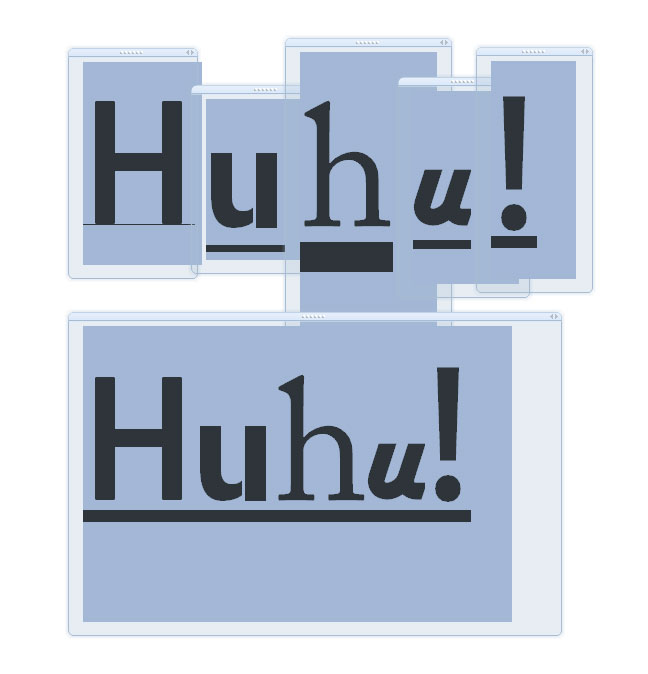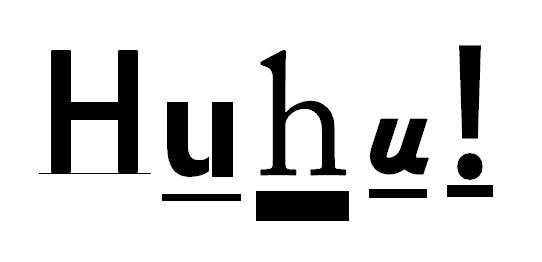
Unterstreichung im Font festlegen?
Gerade habe ich mal eine Grundsatzfrage - kann sein, dass das eine "Anfängerfrage" ist, ich bin bloß grad relativ verwirrt ...
In Office-Programmen oder auch hier im Editor hat man ja die altbekannten Knöpfchen "B", "I" und "U". Während nun bei "I" ja meistens noch vom Betriebssystem ein entsprechender Italic-Font aus der Familie geladen wird, rätsle ich nun gerade, woher dann diese Unterstreichung kommt, da es offensichtlich ja keinen "Underscore-Font" gibt.
Hier muss also scheinbar irgendetwas "klammheimlich automatisch" gemacht werden.
Oder aber: legt man irgendwo im Font fest, wie bei einer Unterstreichung verfahren werden soll?
Es scheint ja nicht irgendwie das Betriebssystem nach Belieben zu machen, sondern die automatische Unterstreichung ist schon durchaus Font-abhängig; hier ein typografisch unglaublich wertvolles Beispiel zu Veranschaulichung:
Könnt ihr mir sagen, wo dazu die "Stellschraube" ist? Bzw. wie das mit dem Unterstreichen eigentlich funktioniert? Wie läuft das ab? Wie kann man da etwas beeinflussen (Lage, Dicke, ...) beim Erstellen eines Fonts?
Im Font kann das global definiert werden – wo ist die Linieund wie dick ist sie.
Dass das alle Hersteller auf sinnvolle Werte einstellen, kann man vermutlich anzweifeln.
Was die Anwendungsprogramme daraus machen, ist unterschiedlich.
Ich hab das jetzt nicht erforscht, aber ich würde annehmen dass in einem Programm das "auf Knopfdruck" unterstreicht das Auslesen dieser Werte sinnvoller ist und deinem Beispiel nach auch funktioniert, während in einem Grafikprogramm, in dem ich als Setzer vermutlich selbst definieren will, wo, wie dick und in welcher Farbe die Schrift unterstrichen wird, diese Sache eher kontraproduktiv wäre. Indesign interpretiert die Vorgaben jedenfalls nicht ...
Komisch, ich habe festgestellt, dass InDesign die Unterstreichungswerte aus die Schriftdatei einlesen und diese richtig umsetzen. Habe es gerade für die TheSerif, FF DIN, Rotis (AT), ITC Garamond (URW) und Minion getestet. Das Zeichen Underscore und der Stil »Unterstreichen« ergeben bei gleicher Schrift die gleiche Striche an gleiche Positionen. Ist aber anscheinend (leider) kein Standard. Bei Arial, Arno und FF Celeste sitzt die Unterstreichung höher als das Underscore …
In QuarkXPress war es in Versionen wie 2, 3 und 4 wie heute in InDesign. In Version 9 sitzen die Unterstreichungen alle woanders, bzw. nicht da wo sie hingehören :–(
Neo-Office und TextEdit richten sich nicht (oder auf nicht nachvollziehbare Weise) nach den Unterstreichungswerte der Schriften.
Die Unterstreichungswerte findest Du in FontLab unter:
File –> FontInfo –> Metrics and Dimensions –> Key Dimensions.
Underline = Abstand von der Grundlinie zur Mitte(!) des Unterstreichungsstriches
Thickness = dessen vertikale Linienstärke
Siehe hierfür auch das „black book“ zu PostScript; ein PDF findet sich irgendwo auf die Adobe Website.
Das einzige was uns dazwischen funkt, ist dass die Unterstreichungsstriche wie Grafiken gerastert werden und nicht wie Schrift. Das heißt, das der Rasterizer (vereinfacht gesagt) alle Pixel die vom Unterstreichungsstrich „getroffen“ werden, schwarz gemacht werden. Deswegen sehen die Unterstreichungsstriche immer etwas fetter aus als gewollt (zwischen 1 und 2 Pixel der Auflösung des Ausgabegerätes). Bei Schrift wird das Ergebnis vom Rasterizer korrigiert. Das lässt sich nachvollziehen wenn man in die Schrift ein Underscore anlegt, dessen Werte die des Unterstreichungsstriches entsprechen. Dann Schrift generieren und In InDesign anschließend ein Testdokument anlegen wobei du abwechselnd Underscore und unterstrichene Zeichen aus der angelegten Schrift setzt. Et voilà!
Interessant wirds dann nochmal, wenn ich die verschiedenen Schriftarten "in einem Wort" schreibe, statt einzelne Buchstaben: dann wird irgendwie eine einheitliche Unterstreichung benutzt:
Habe das im OneNote schnell geschrieben: oben die Buchstaben einzeln, unten die Buchstaben zusammen in einem Wort.
Es wird hier also anwendungsspezifisch scheinbar doch irgend ein Automatismus bemüht - und evtl. irgendwie ein Durchschnitt errechnet?
Das "Black Book" von Adobe, ist das zufällig das hier: T1 Spec? (Bin durch diese Seite drauf gestoßen.)
Btw: Wie würdet ihr eigentlich "handwerklich korrekt" unterstreichen? So in Anbetracht dessen, da diese Automatismen ja immer gern die Unterlänge der Buchstaben unschön durchschneiden?
Ja, genau! Findet sich aber auch irgendwo bei Adobe
Am besten gar nicht! Unterstreichungen sorgen dafür dass die Unterlängen weniger auffallen, deshalb verringert sich die Leserlichkeit unterstrichener Worte. Wenn überhaupt, dann ohne durchstreichen der Unterlänge. Geht wie folgt: Schriftdatei mit FontLab, Glyphs oder ähnlich öffnen, Width (Dickte) des Space (Wortabstand) aufschreiben. In InDesign vor und nach den Zeichen mit Unterlänge einen Wortabstand einfügen. Die Wortabständ mit der gleichen Anzahl der Einheiten wie Space unterschneiden. Das geht, weil InDesign (und Illustrator) genau die gleichen Einheiten wie PostScript und die meisten OpenType Fonts verwendet. 1000 pro Geviert. Bei Quark sind es (wenn das Standard Geviert in den Preferences eingeschaltet ist) 200 pro Geviert. TrueType-Fonts und OpenType mit einer höheren Auflösung müssen auf 1000 Einheiten runterskaliert werden um den für InDesign richtigen Wert zu erhalten. Die runterskalierte Schrift nicht sichern :–). Funktioniert nicht in Blocksatz …
Wenn ich das ganze nach HTML exportiere und mit dem Feuerfuchs anschaue, sieht die Dicke der Unterstreichung eher wie definiert aus ... Position muss ich mal genauer ausmessen bei Gelegenheit, könnte aber grob hinkommen bei beiden ...